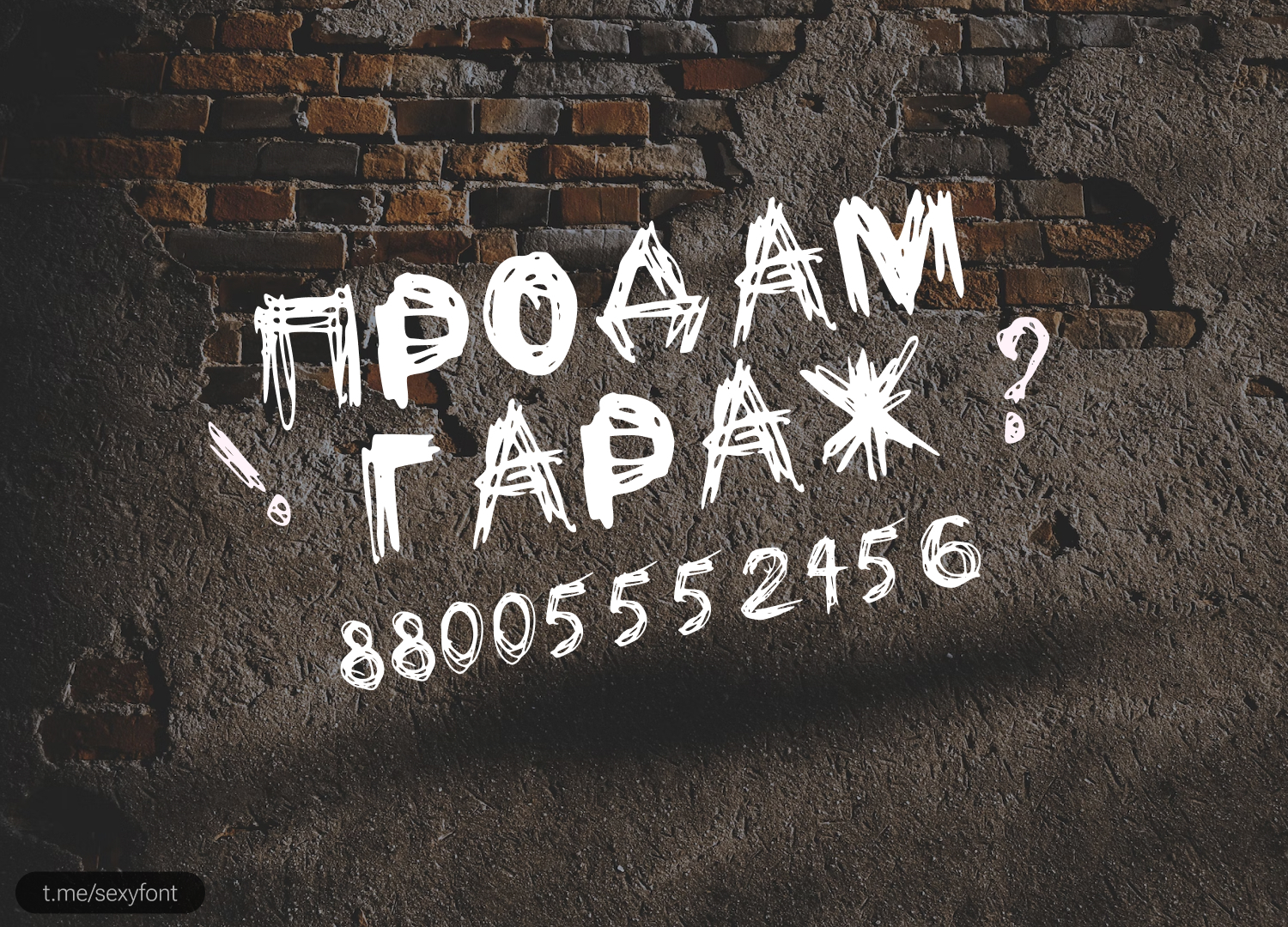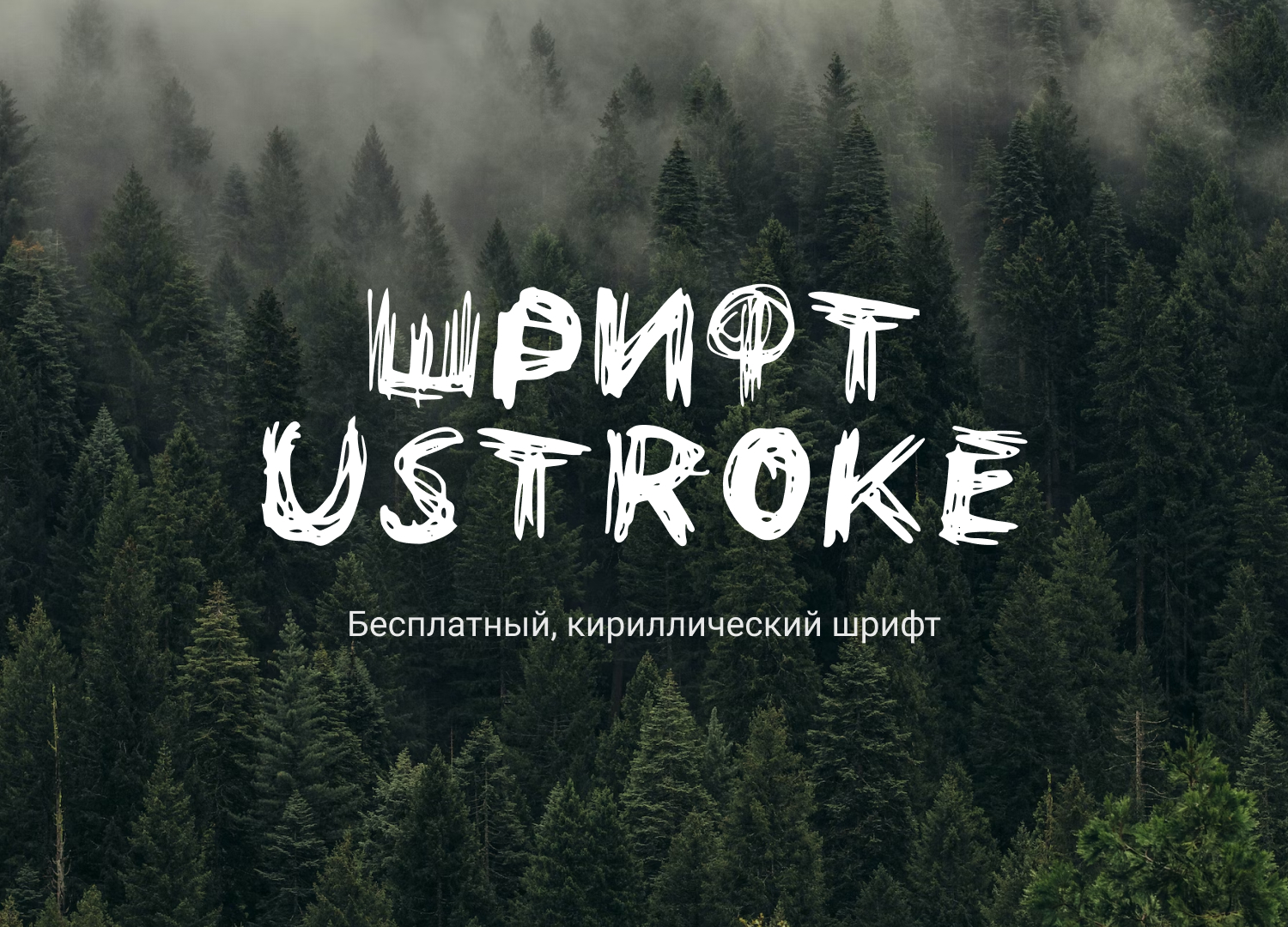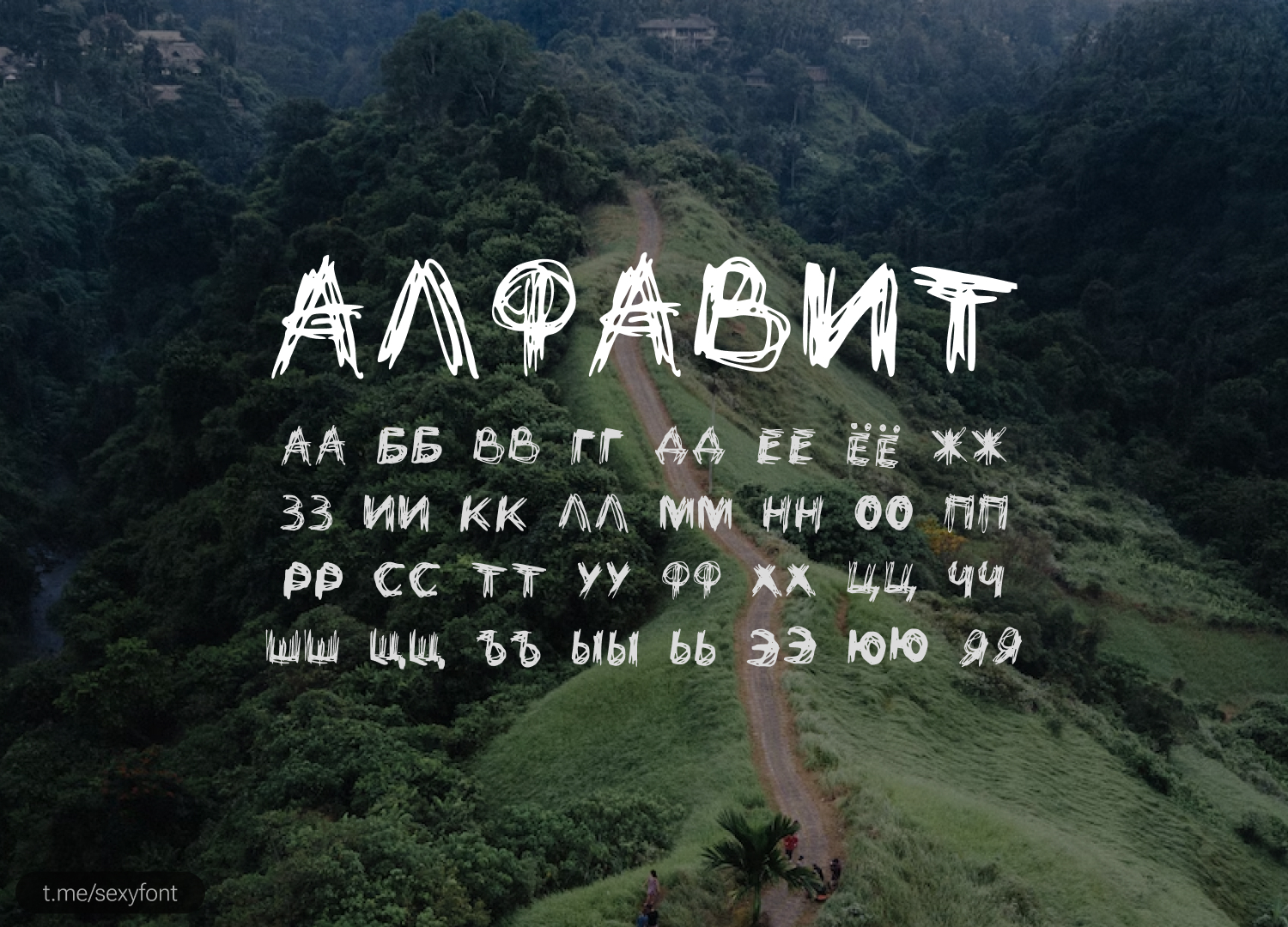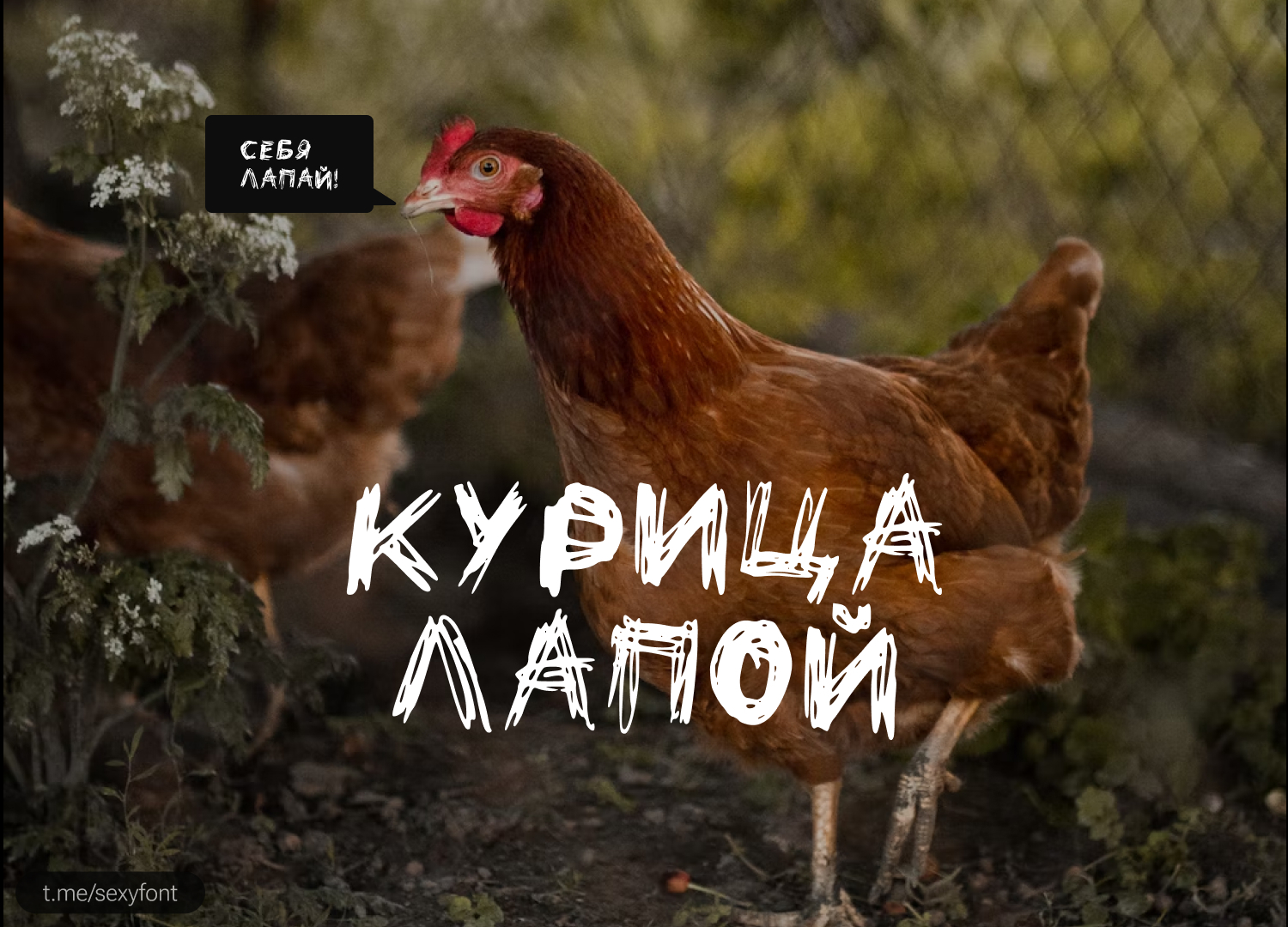
Шрифт ustroke rough
Веселый и почеркушный шрифт) Шрифт ustroke rough, нарисованный от руки, имеет неровный, колючий вид, что делает его уникальным даже среди других шрифтов, нарисованных от руки. Формат файла - TTF, содержит прописные буквы, цифры и поддерживает латинские и кириллические символы. Автор: Tikhon Reztcov. Бесплатно для всего.